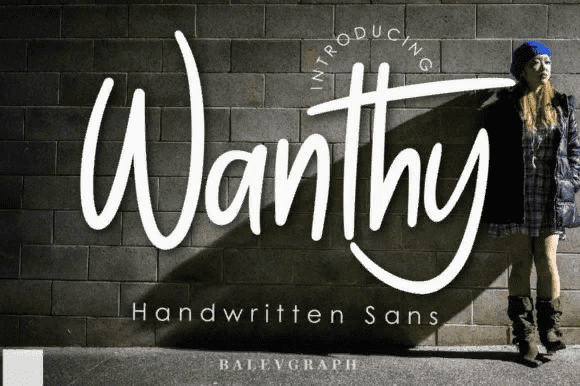
Название: Wanthy Font (2021)
Wanthy - это современный шрифт, удобный для чтения, смелый и стильный.
Он имеет плавные изгибы и идеально подходит для модного брендинга или редакционного дизайна.
Смело добавляйте его в свои проекты, и вы будете в восторге от результатов.
Название: Wanthy Font (2021)
Wanthy - это современный шрифт, удобный для чтения, смелый и стильный.
Он имеет плавные изгибы и идеально подходит для модного брендинга или редакционного дизайна.
Смело добавляйте его в свои проекты, и вы будете в восторге от результатов.